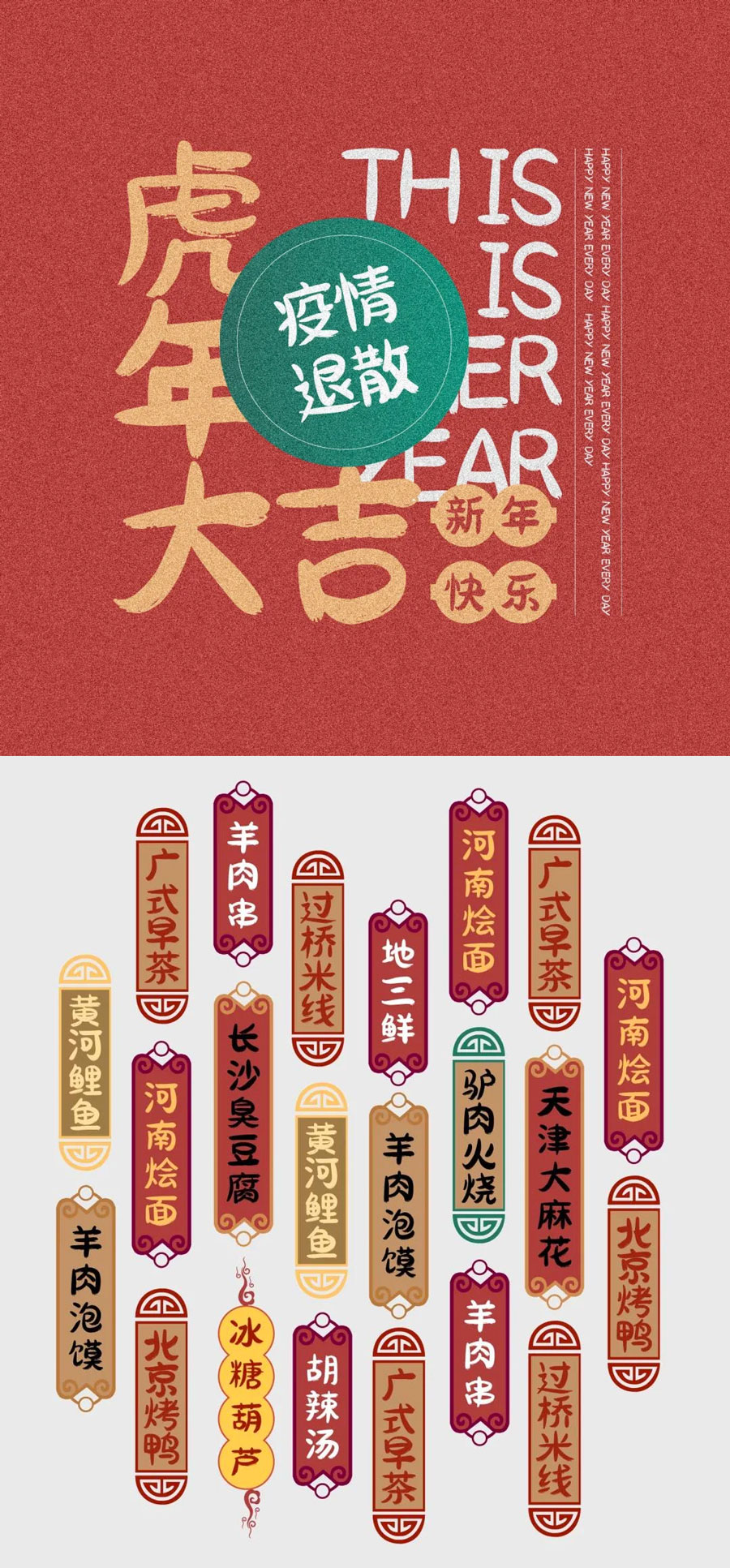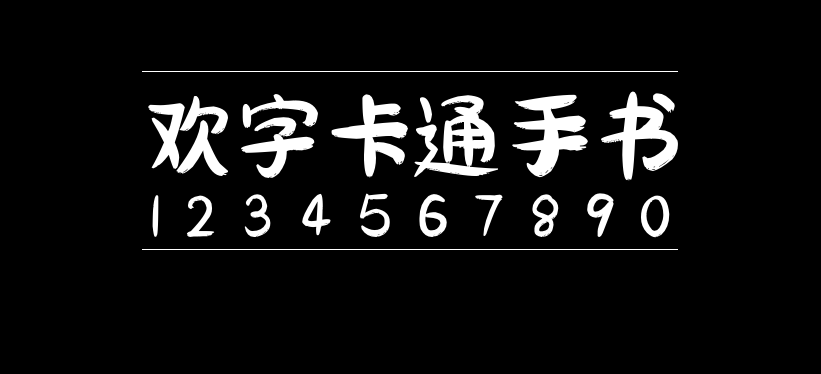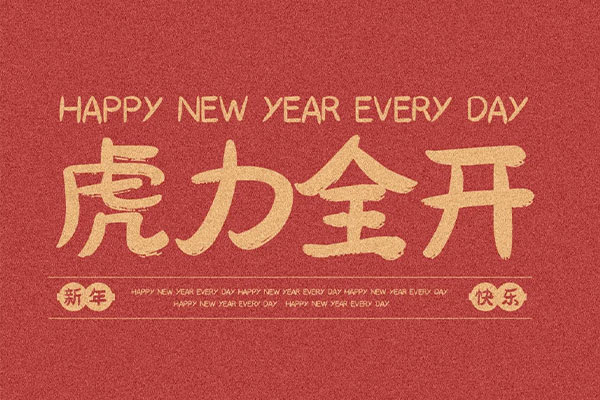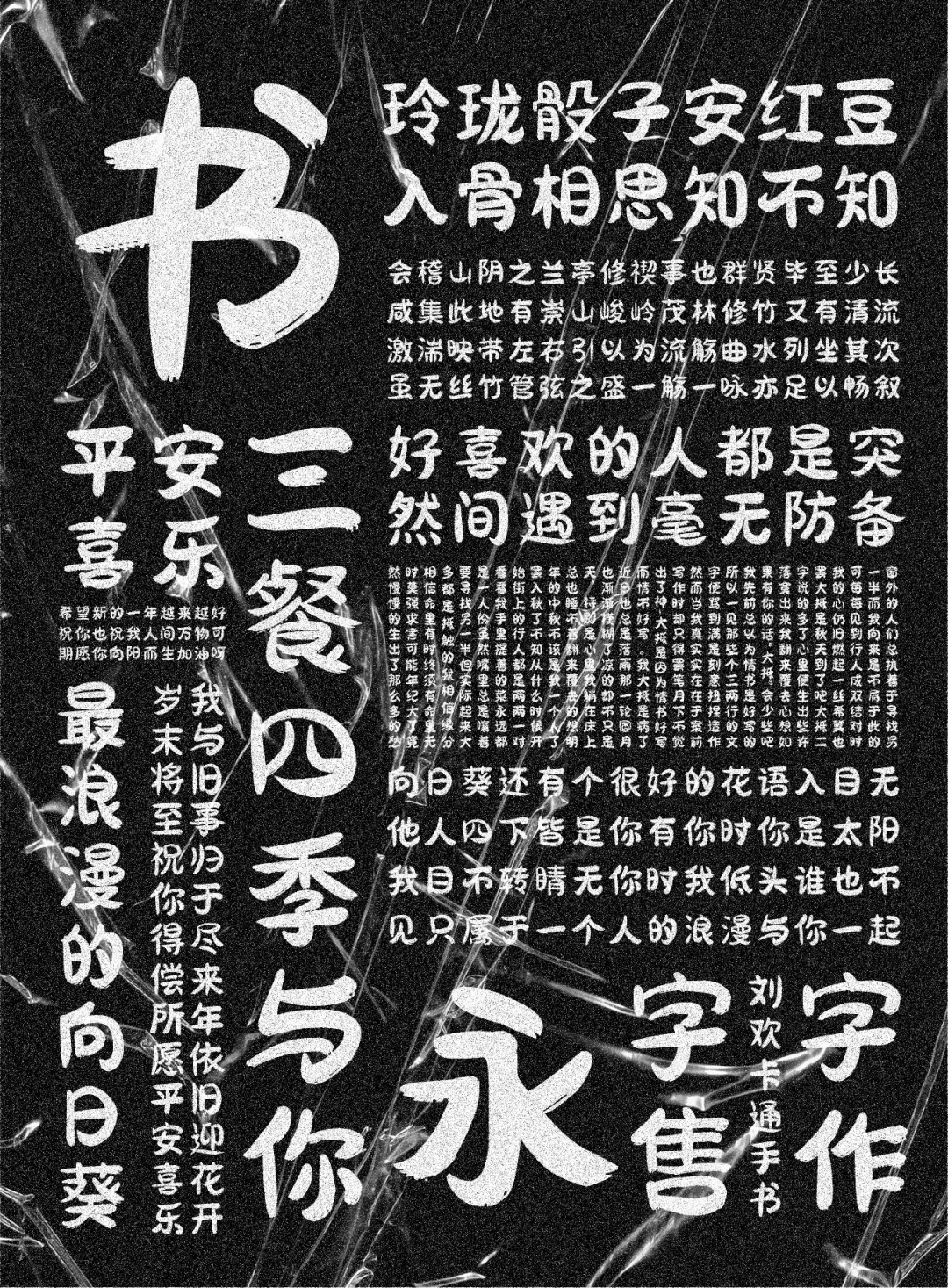
欢字卡通手书
欢字卡通手书的作者是中国大陆的刘欢同学,创作的动机据作者称是因为没找到合适的工作,又闲着无聊涂涂画画,萌生了做字体的想法,该字体也是作者的第一款中文字体。
欢字卡通手书已包含简体标准的6763字,不会存在缺字现象。该字体由作者在公众号发布,并声明永久免费商用。
以下为字体发布介绍的原文引用:
2018年初,接触到字体设计,就被汉字的演变深深吸引,一向不爱写字的我才发现:原来汉字还可以这么美!
其实说起这套字库的创作初衷,是因为当时找的工作不合适然后回家了…
当时实习选择去了离家还算近的上海。全球最现代化的大城市之一,纸醉金迷的大上海,繁华程度已经超过东京和纽约。土狗进城,见到了很多新奇的事物,不愧是很多年轻人向往的魔都!
一个没见过世面的农村小伙子,见到了繁华的夜都市和车水马龙,以及熙熙攘攘的业界精英。我也想过在上海拼搏闯出一片属于自己的小天地,奈何实力不济,上漂了不到两个月,找不到自己适合的工作,最终还是回家了。
与其说,不合适,其实还是自己没有足够的实力,哈哈。也许,每个有血性的年轻人都是这样吧,见到了大城市的繁华又怎么甘心回到小县城呢。
到家以后,父母和亲戚都为我的工作而着急,都21岁了天天待在家里,邻居会怎么看?我想要提升自己的水平方便以后找工作,就以考完驾照再出去的理由在家顺利待了一段时间。
就是那段时间,在家疯狂恶补版式、插画、剩下时间就是练字了。
事实证明,在家待久了,确实被邻居嘲笑了……然后父母也不能理解自己。不出去找工作,每天在家乱写乱画的有什么用,为此也争吵了很多次……
欢字卡通手书
沟通不了,还是想着能提升自己最好。继续待在家里!也可以说是写字让我有了对未来憧憬的动力。
说起字库,对于知识产权,版权问题是不可避免的,刚入门的设计师,难免会因为不懂版权,对自己或对公司而言,这几年的版权新闻巨额罚款也是不断出现,造成不可挽回的损失。想着写了就写一套字库出来,也算为社会尽自己的绵薄之力。
既然决定了就开始,每天除了吃饭就待在屋里写字,顶着压力,写了又写,改了又改,写了几种字样,最后定了这一款卡通字体。到2020年12月初全部写完。
到月底拿着自己的这套字库在测试的时候,开心的一整晚没睡着!
现在只想对当时的自己说:孤独是常有的,兴趣和理想却不是,小时候的梦想好多好多,现在你还记得吗?一个人前行时,什么都可以丢弃。目标不能丢,耐受不了寂寞,咸鱼翻身的机会都少有。
下面来看字体展示,起名“卡通”字体,其实用作“标题字”也是OK的。
所有笔画以“圆润”为主,保留少量飞白,在屏幕上显示更佳。
同时在线下使用也不缺失手写韵味。
该字库不限制使用场景,印刷书籍除外,不适合太小的字体展示。